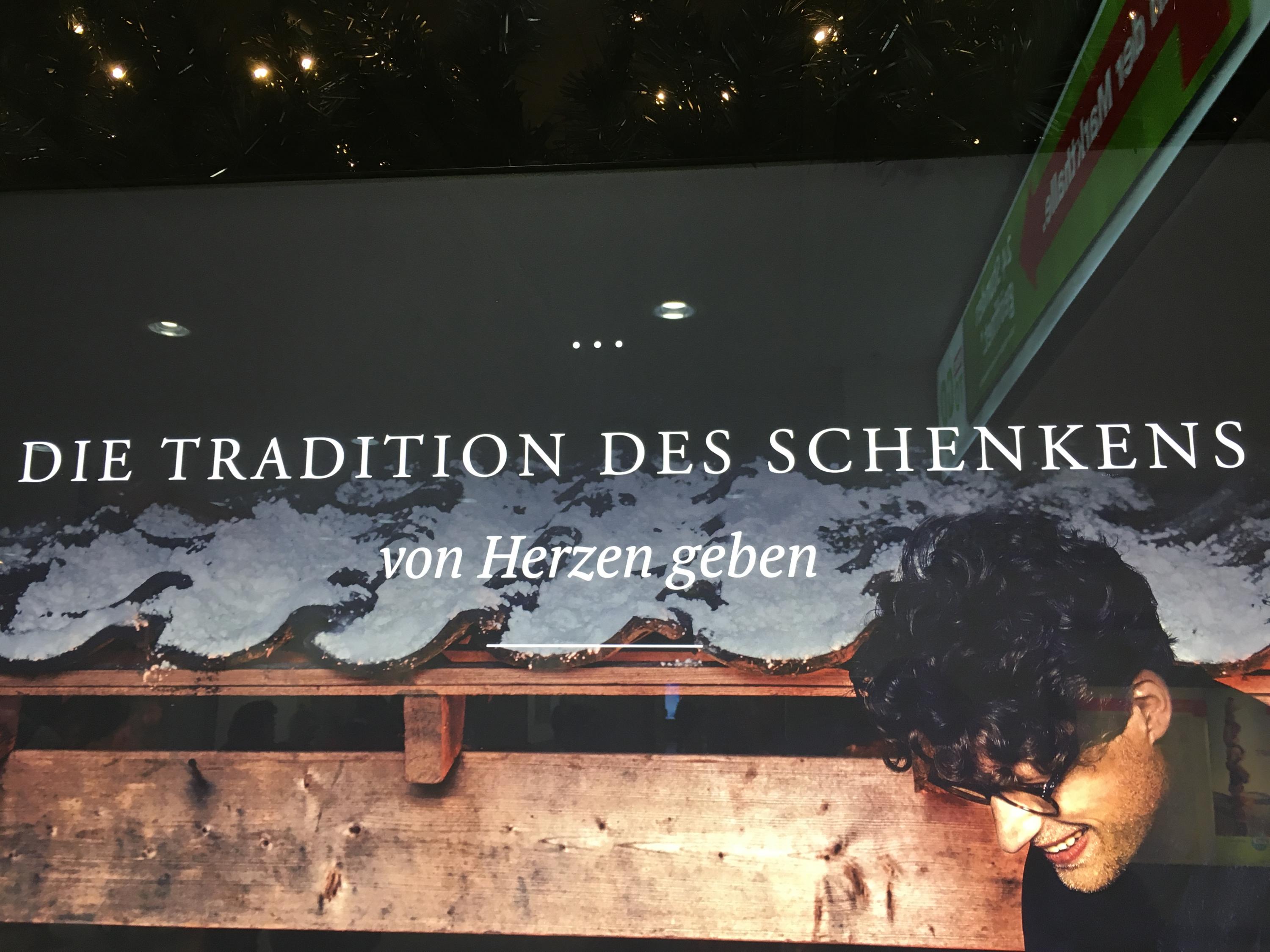
Hausschrift (Retail) von "Rituals" gesucht
ich suche folgende Schrift. Sie wird im Retail-Bereich der Rituals-Filialen genutzt, unterscheidet sich aber von der Antiqua, die sie auf der Website nutzen.
Da hat der Messebauer einfach eine Garamond genommen :-)
Der scheint auch gestalterisch sehr ambitioniert zu sein: Die Kursive ist eine ganz andere (also weder Garamond noch Mrs Eaves).
Erinnert mich spontan an die Merriweather, die hat aber kein komplexes g.
Das ist die PT Serif :-)
Hat jemand eine Idee, um welche Schrift es sich bei der Kursiven handelt?
Merriweather kommt dem schon Nahe, ist aber, aber leider nicht 100%.
Aber warum nimmst Du nicht die Mrs Eaves, welche RITUALS (zumindest fürs Web) eigentlich verwendet. Die anderen scheinen nur ein Kompromiss-Versuch des Dienstleisters zu sein, da die Mrs Eaves eventuell nicht vorlag. Wenn man mit der CC unterwegs ist, kann man diese aber problemlos synchronisieren.